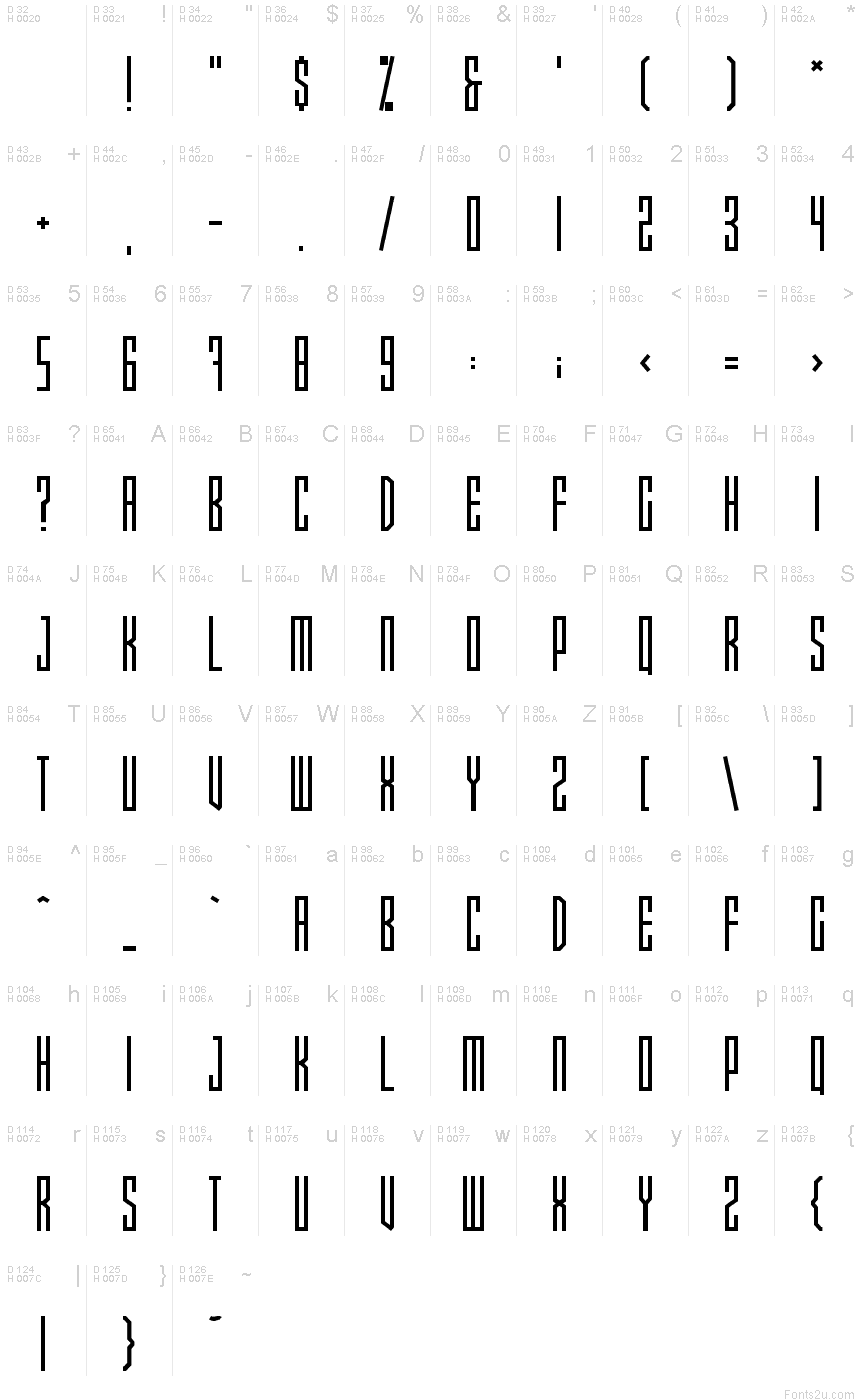
خط Xray Ted من تصميم Jakob Fischer هو خط مجاني من فئة "Display" ذات الطابع التقني (Techno)، يتميز بأحرف كبيرة شاهقة ذات هياكل مقسمة وأسلوب مستوحى من أفلام الخيال العلمي الكلاسيكية. الحروف ضيقة ومستقيمة، ومبنية من أشكال عمودية ثقيلة تقطعها قنوات بيضاء رفيعة، مما يمنح الخط إيقاعاً يشبه الأشعة السينية أو الماسح الضوئي، بعيداً عن اللمسات الهندسية التقليدية الملساء.
هذا يجعله خياراً طبيعياً لعناوين الملصقات، وشعارات الألعاب، ومنشورات "السينثويف" (Synthwave)، وأغلفة المجلات المستقلة، وعناوين الأفلام حيث تتطلب الكلمات القليلة نبضاً ميكانيكياً قوياً. وبما أنه خط مجاني، فهو مناسب أيضاً للشعارات (Monograms) وتصاميم العلامات التجارية القصيرة، حيث تضفي التقطيعات الداخلية المتكررة على الأحرف الأولى لمسة مستقبلية ذات طابع تقني.
Xray Ted